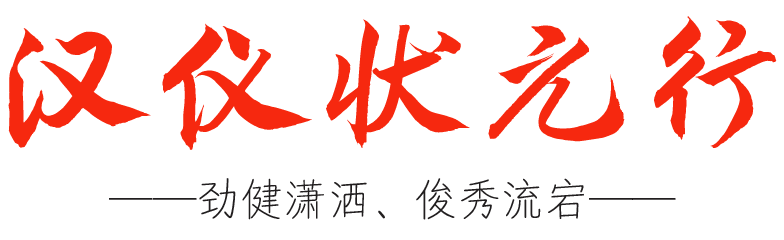
汉仪状元行字体介绍,用字体为高考加油助威!
汉仪状元行是由汉仪字库签约作者聂国强老师创作的一款劲健潇洒的行书字体。这款字笔锋浏明亮、运笔洒脱、动静相应、粗细兼备,使其能够在在保留毛笔书写古意的基础上,传递出飒爽流畅的气场,烘托出热情洋溢的气氛。而统一的字面和规范的书写字形,又使得这款字相较于一般的行书字体有着良好的识别度。该字体适合作为标题字,用在宣传助威、文艺表演、公益活动、文化周边、节日庆典等场合,以营造传统、活力、激情、喜悦的氛围。
聂国强,本科、硕士毕业于中央美术学院。博士毕业于中国艺术研究院。现为中国书法家协会会员、山东工艺美术学院书法专业教师。
作者在创作时有意识地考虑到平面设计师使用字体的需求。这款字体有着较高的风格一致性,字面成正方形,大小、形状、位置与灰度相对均匀,使得字体在标语、横幅等场合无需做复杂的排版,直接敲出文字就能得到较为均衡的间距与视觉效果。
该字体每一个字形都选择了常见的标准规范的写法。虽为行书但笔意明朗、曲直分明。使得字形有着较高的识别度。
为了让这款字体更能适应标题场合,该字体的笔画有着丰富的提按变化。部分笔画赋草于真、笔直劲健的运笔和强势有力的顿笔让字形更富力道。而充满力度变化的运笔使得一字之内笔画粗细有轻有重,粗细对比明显,强化了字形的标题效果。
作者在书写时将字形结构处理的较为紧凑,中宫微收、重心平稳、偏旁部首揖让得度,笔画从容地向四周伸展。牵丝映带,潇洒流畅,有如翻江倒海之势,增强字形的表现力。
汉仪状元行的西文部分采用了一种较为潇洒流畅的Italic风格字体做匹配。字形由钢笔写就而成,大写字母造型饱满、夸张、充满弹性;小写字母细腻、优雅、有流动感,能传达出同中文一样的既传统又富有活力的印象。